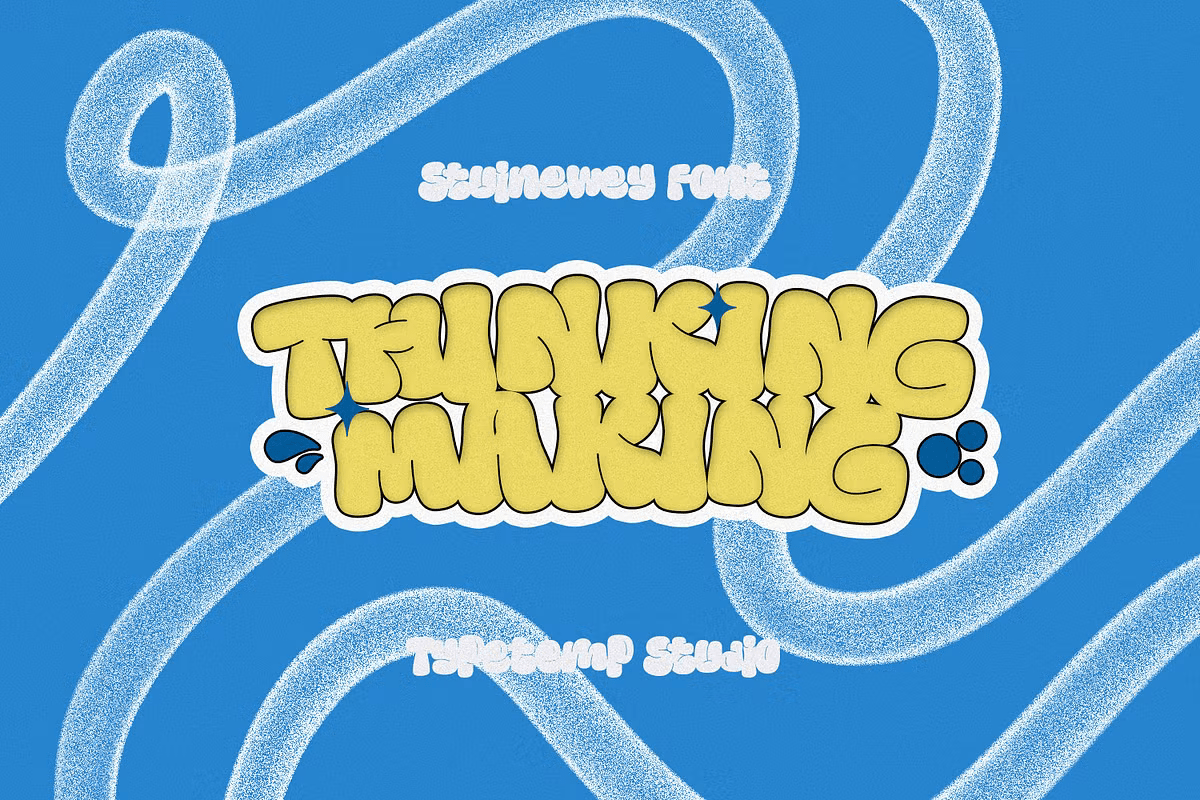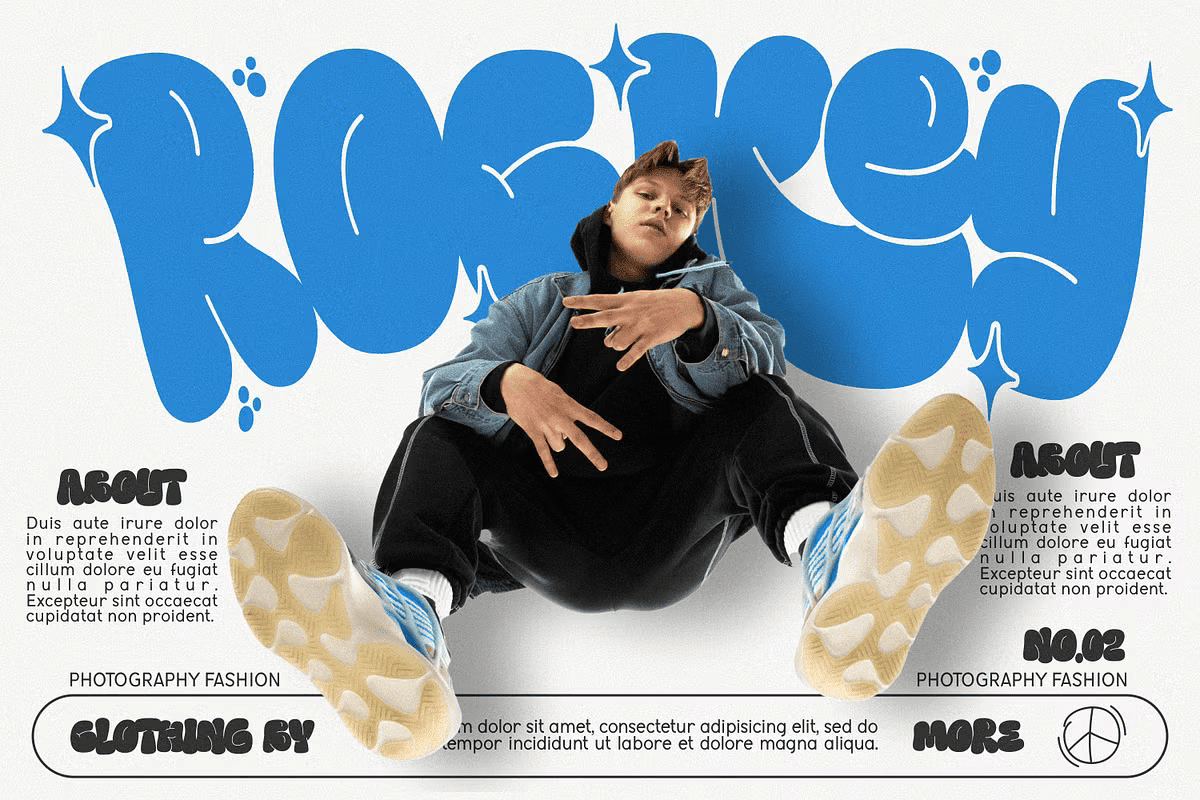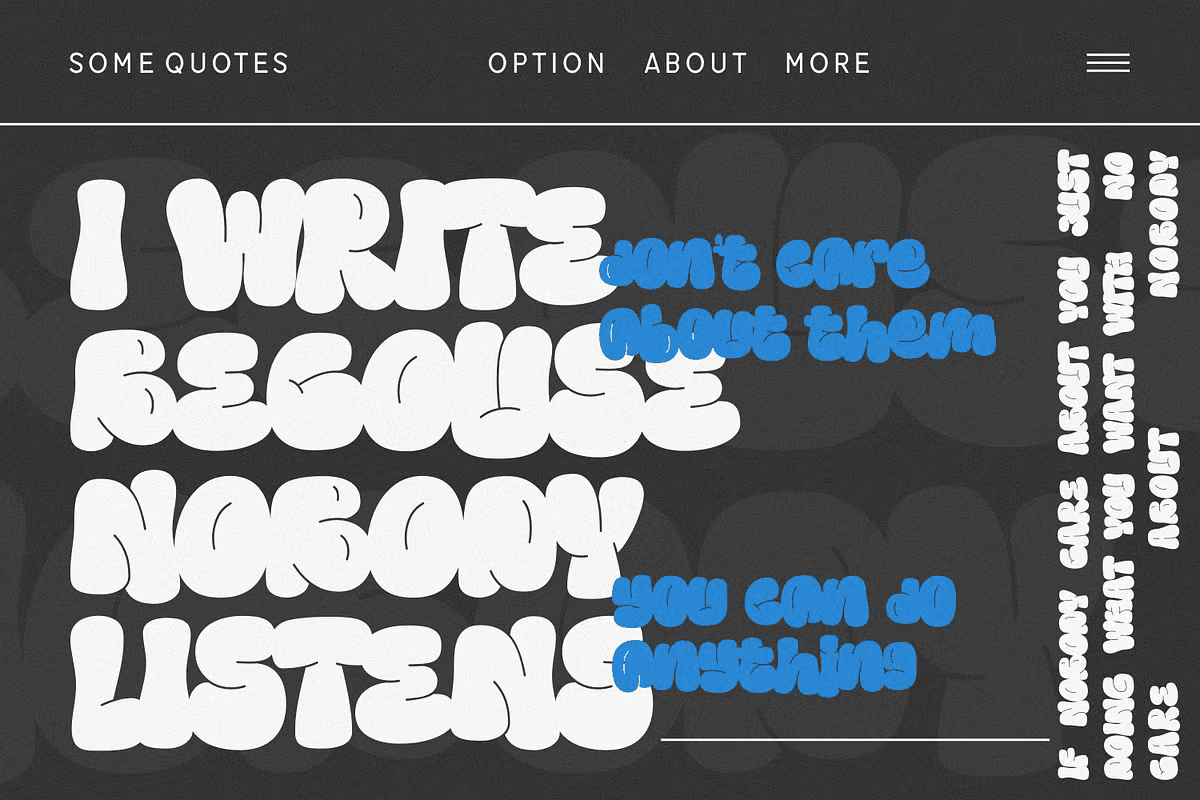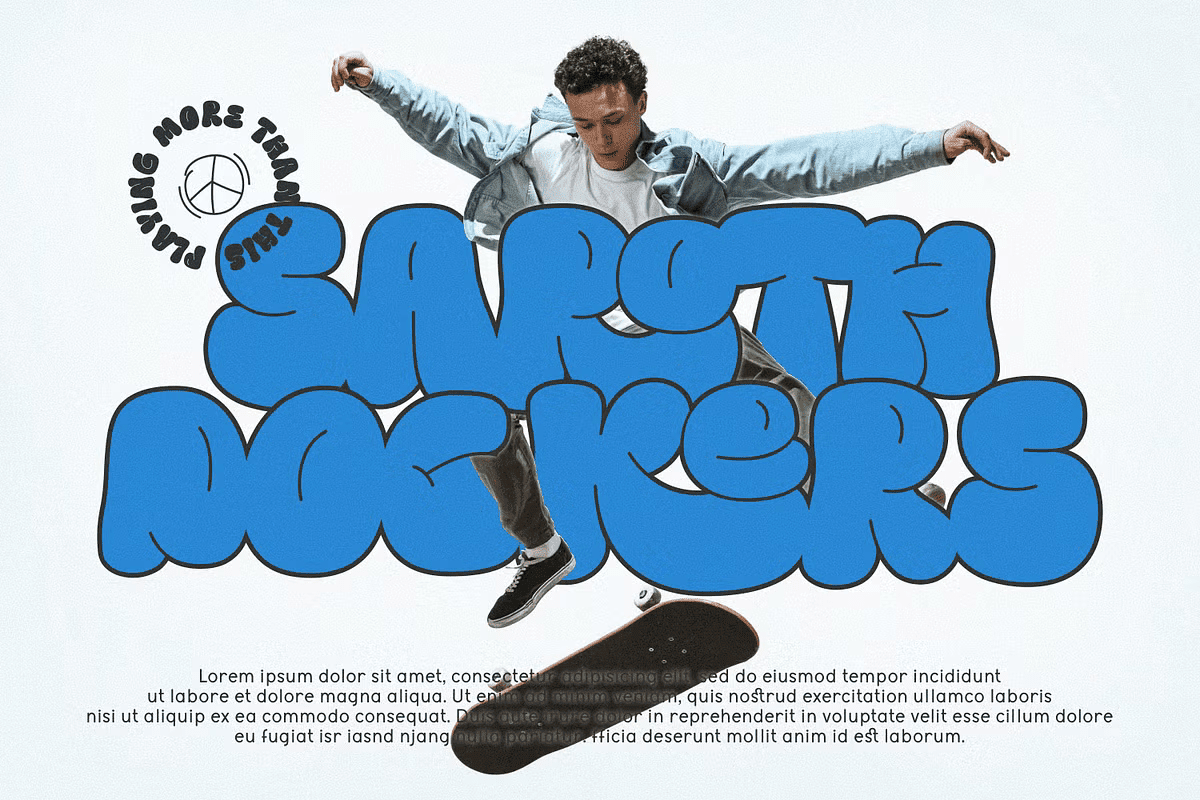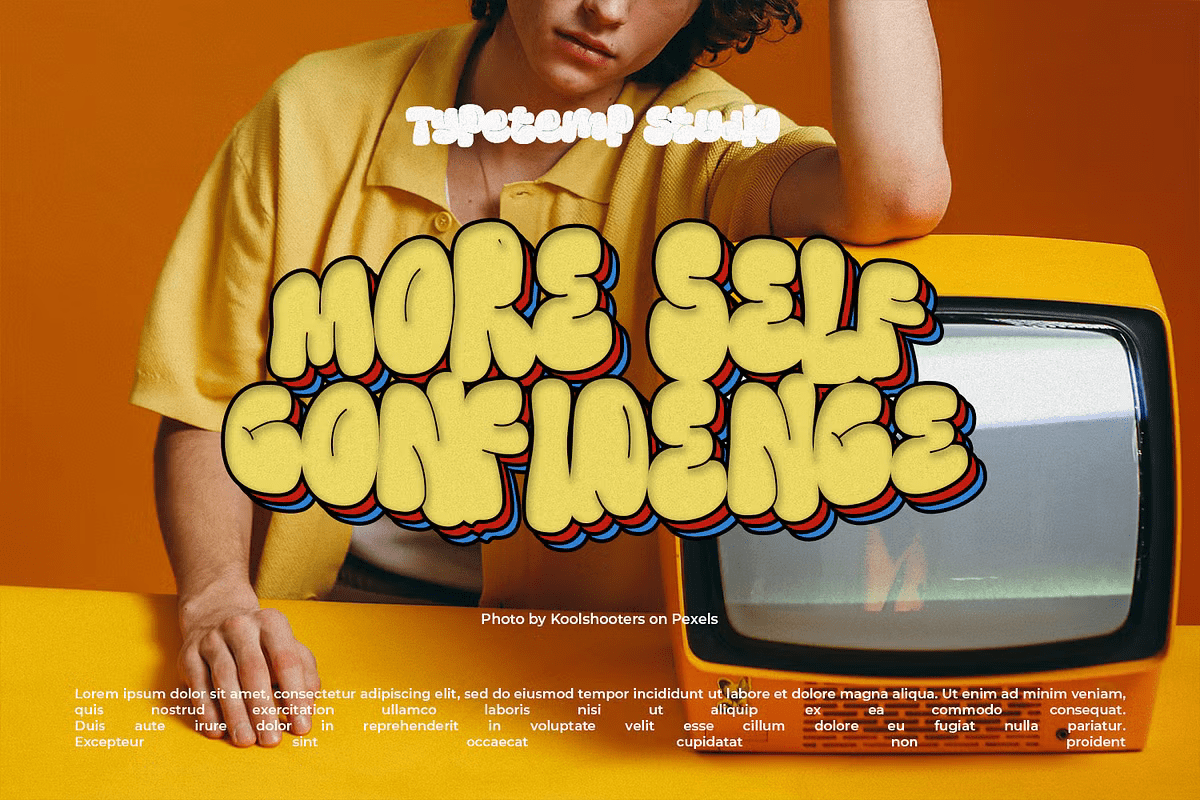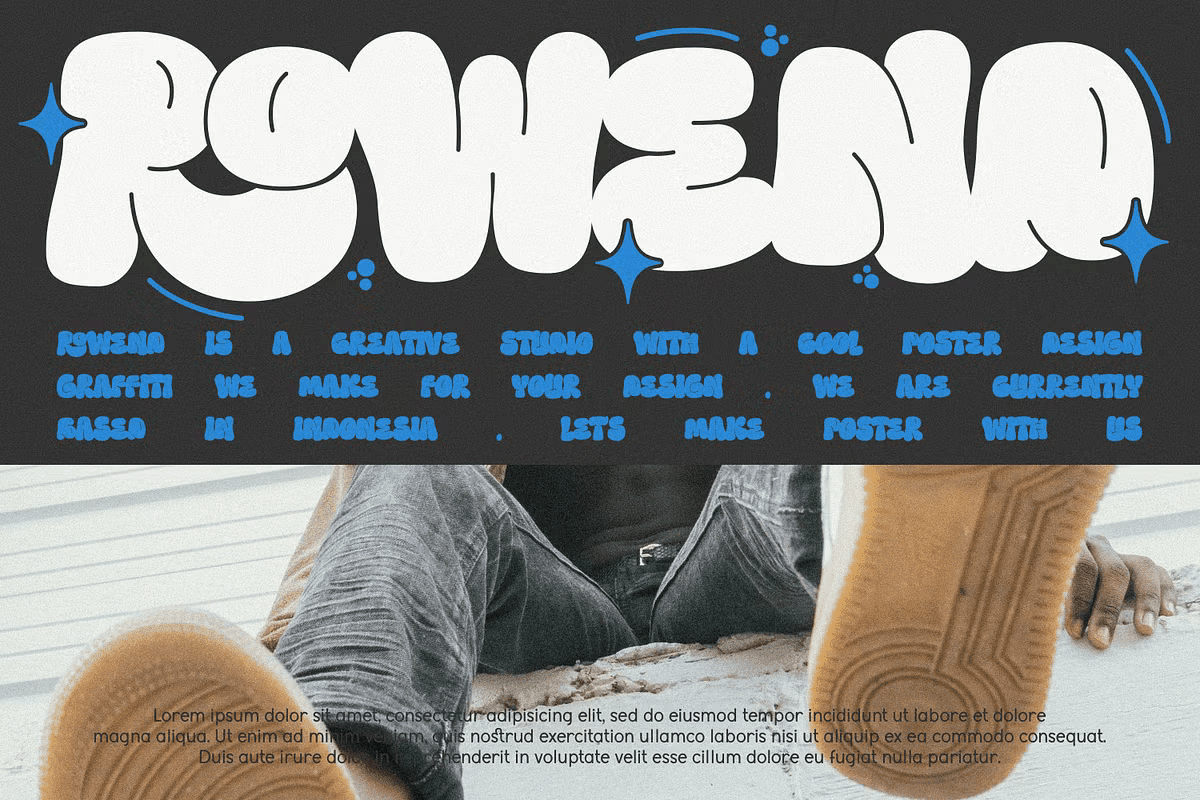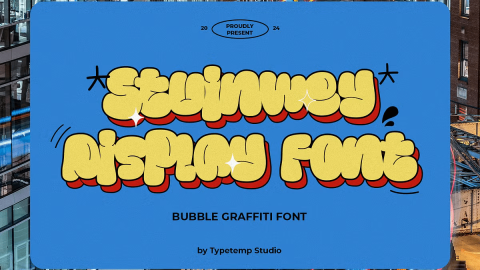
Stuinwey – Bubble Graffiti hiển thị một kiểu chữ với phong cách Graffiti Bubbles. Đi kèm với các lựa chọn khác và liên kết, giúp tạo ra những Poster tuyệt đẹp, thương hiệu, áo thun, đồ họa mạng xã hội và nhiều hơn nữa.